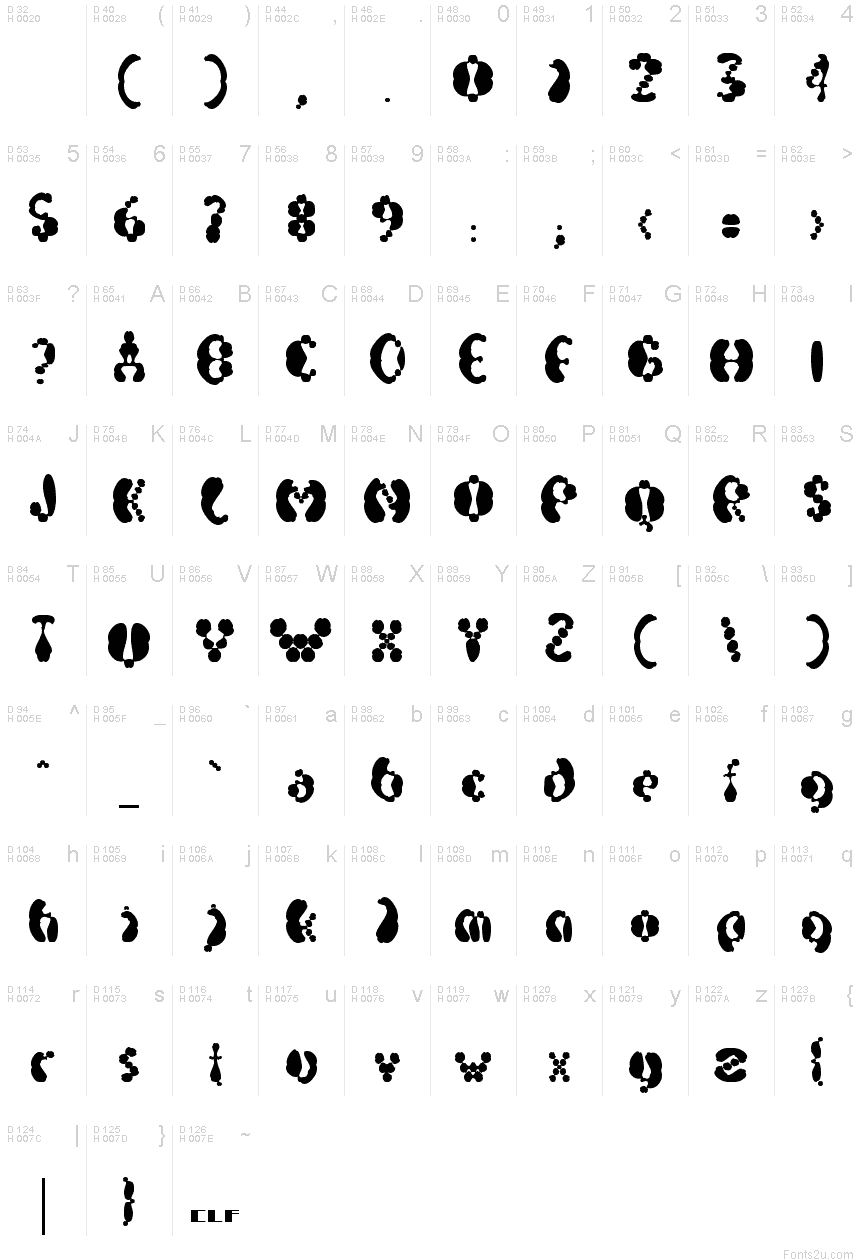
خط Electrack Sweet من تصميم براد بارهام هو خط عرض زخرفي مجاني، بحروف تبدو كأنها مسكوبة وليست مرسومة؛ بقع حبر سميكة تتخللها فتحات دائرية ونتوءات غريبة. يتمتع الخط بطاقة لزجة ومخدرة (سايكدلية)، تشبه مزيجاً بين مصابيح الحمم البركانية وعروض الكرنفالات، مما يحول أي كلمة بسيطة إلى مشهد بصري لافت. تبدو الأشكال الضخمة لعائلة Electrack في أفضل حالاتها عند استخدامها بأحجام كبيرة، حيث يمكن لكل قطرة وبقعة حبر أن تتنفس حقاً.
باستخدام Electrack Sweet، يمكنك دفع عناوين ماراثونات الرعب، ونشرات حفلات الهالوين، وملصقات الحفلات الموسيقية، وأغلفة الألبومات التجريبية، وعلامات غرف الهروب، أو شعارات الألعاب المستقلة إلى آفاق غريبة ورائعة. يعمل هذا الخط المجاني بشكل ممتاز عند استخدامه حصرياً للعناوين مع إقرانه بخط sans serif بسيط جداً للنص الأساسي، مما يجعل الأشكال السائلة والجامحة في مركز الاهتمام.